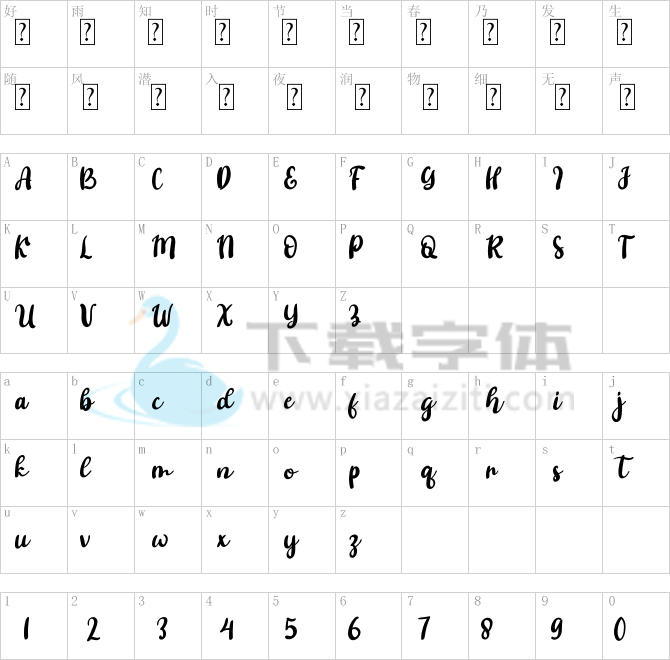
Ashifa.otf字体下载
Ashifa.otf字体下载,这款字体结构工整、笔画清晰,兼顾美观与易读性,适用于标题、正文、海报、包装、LOGO 等多种场景。字形优雅稳定,风格百搭耐看,适配日常排版与创意设计,让文字呈现更舒适、更具质感。Ashifa.otf字体下载一笔一画,皆是细节,以均衡的比例、流畅的线条打造舒适视觉体验,字形端正大气,风格简约现代。无论是商业设计、品牌宣传还是日常排版,都能轻松驾驭,让文字更有格调与力量。Ashifa.otf字体下载字体下载。